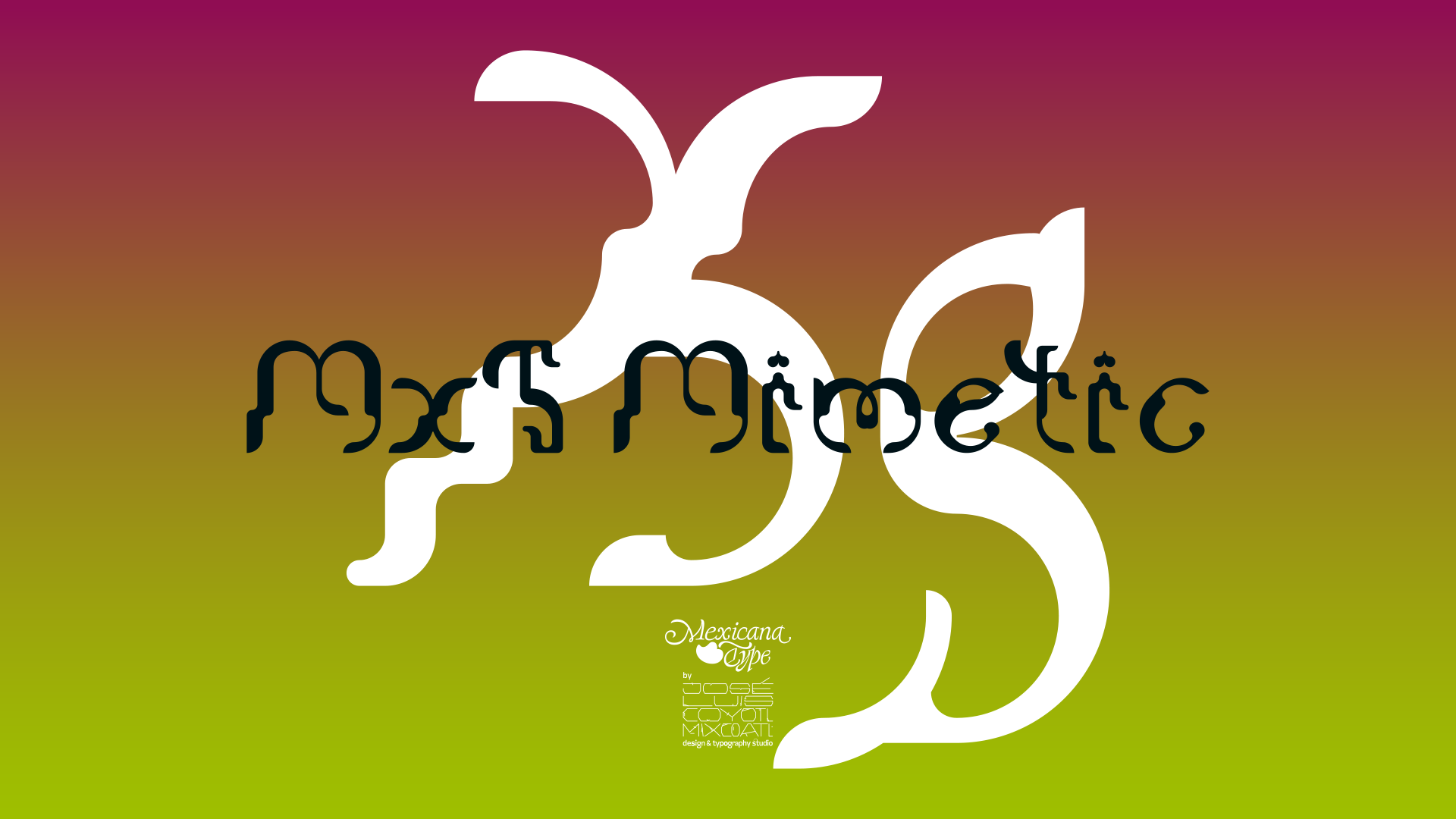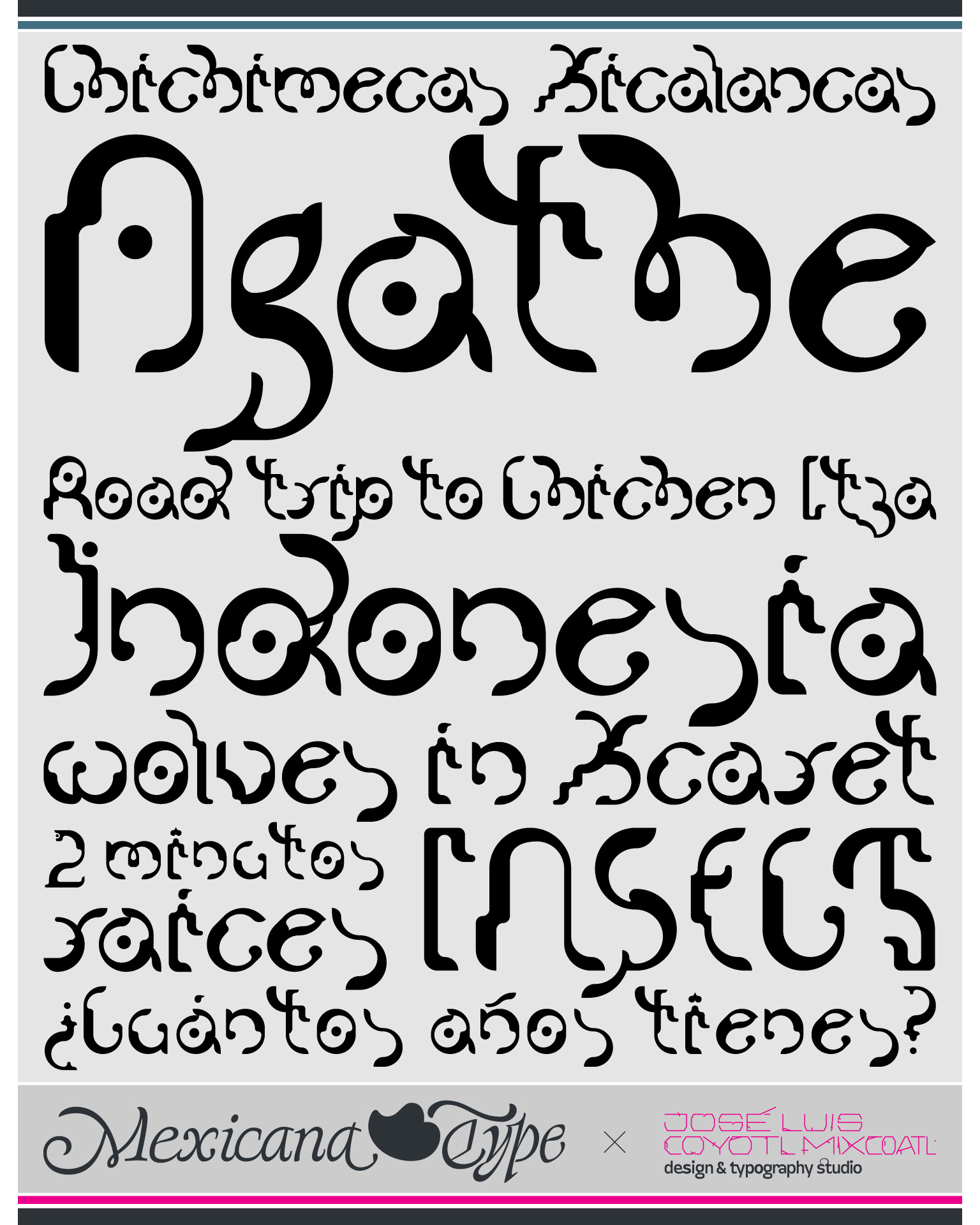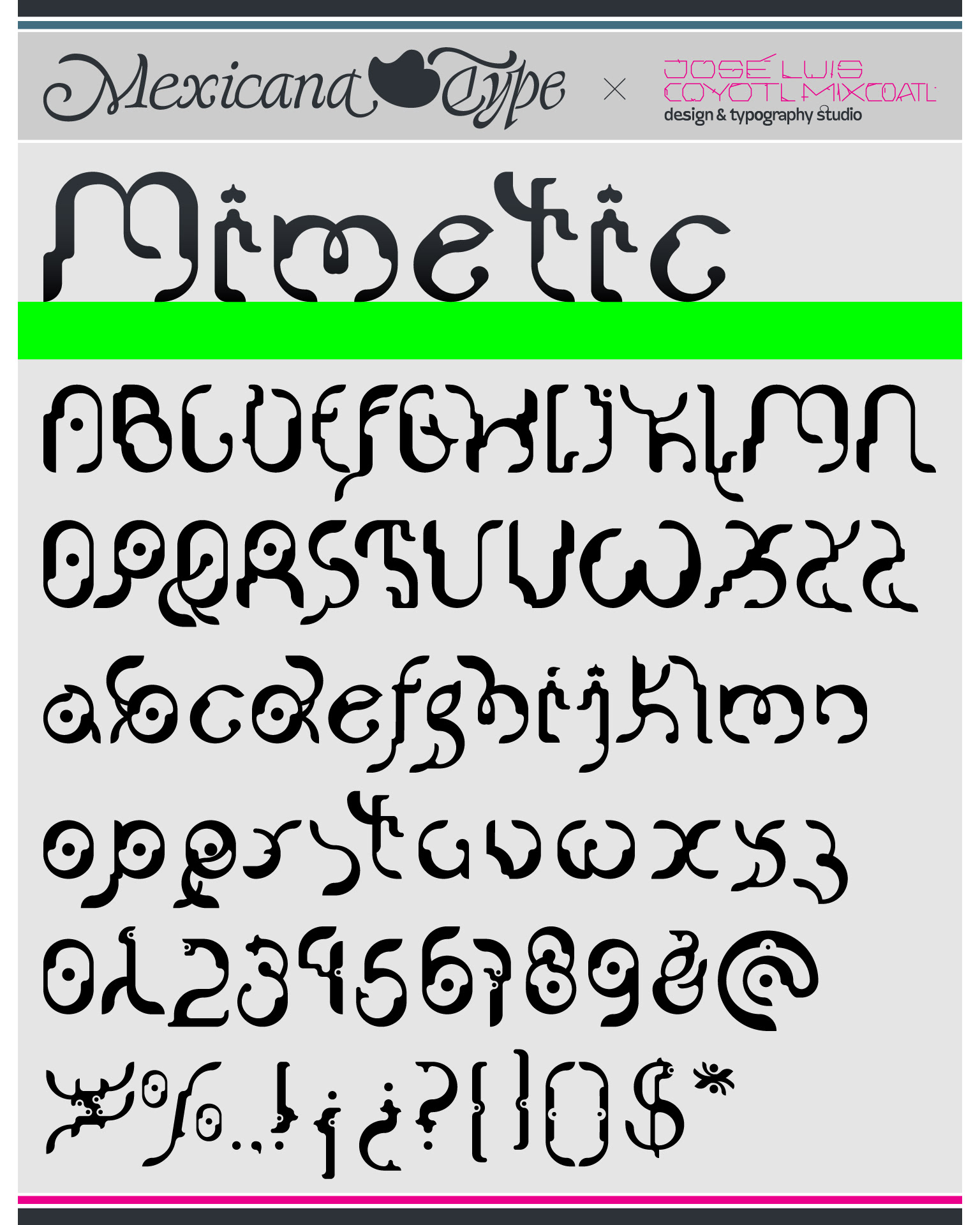
MxT Mimetic es un proyecto realizado en mis primeros años desarrollando tipografía mientras estudiaba la Licenciatura en Diseño Gráfico, con la idea de generar elementos tipográficos ornamentales al inicio, pero eventualmente terminó formando un set de caracteres para poder usarse con un sentido alfabético de lecturas cortas, principalmente con influencia de escrituras como el devanagarii y hebreo, con reminiscencias a formas orgánicas y un tanto miméticas y experimentales, generando textos con una amplia variedad de formas y contraformas en su composición de textos, haciendo un display interesante y lleno de posibilidades en sus usos.